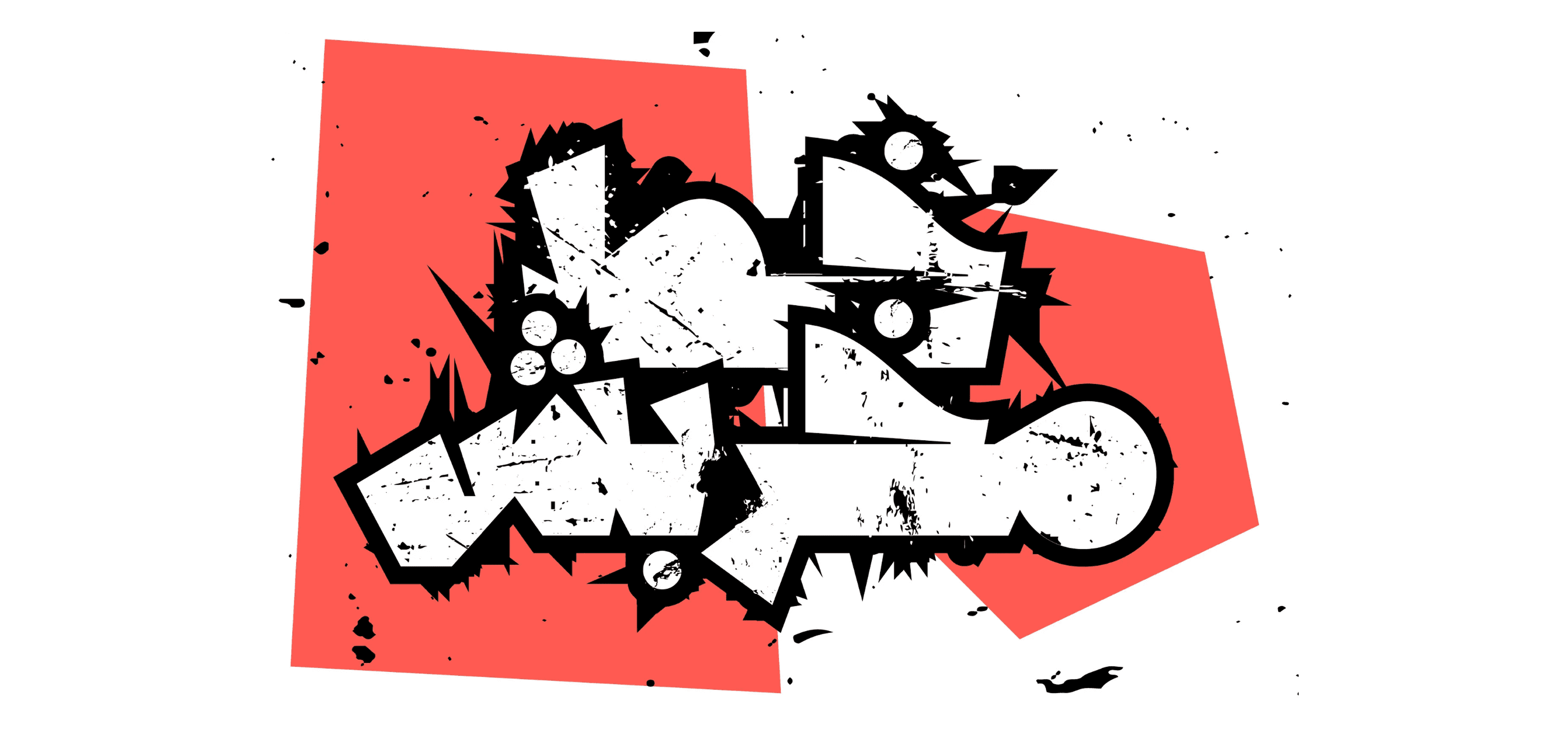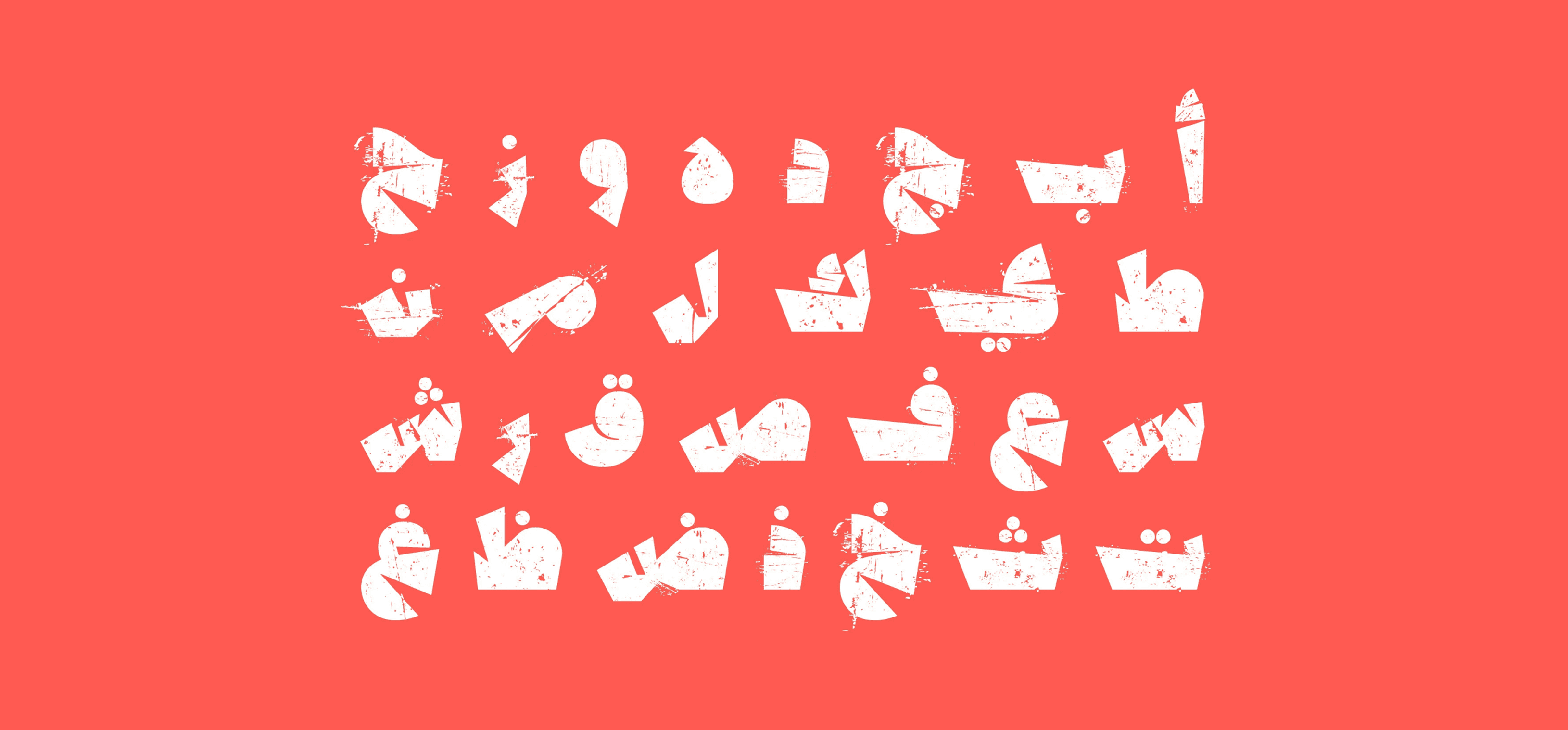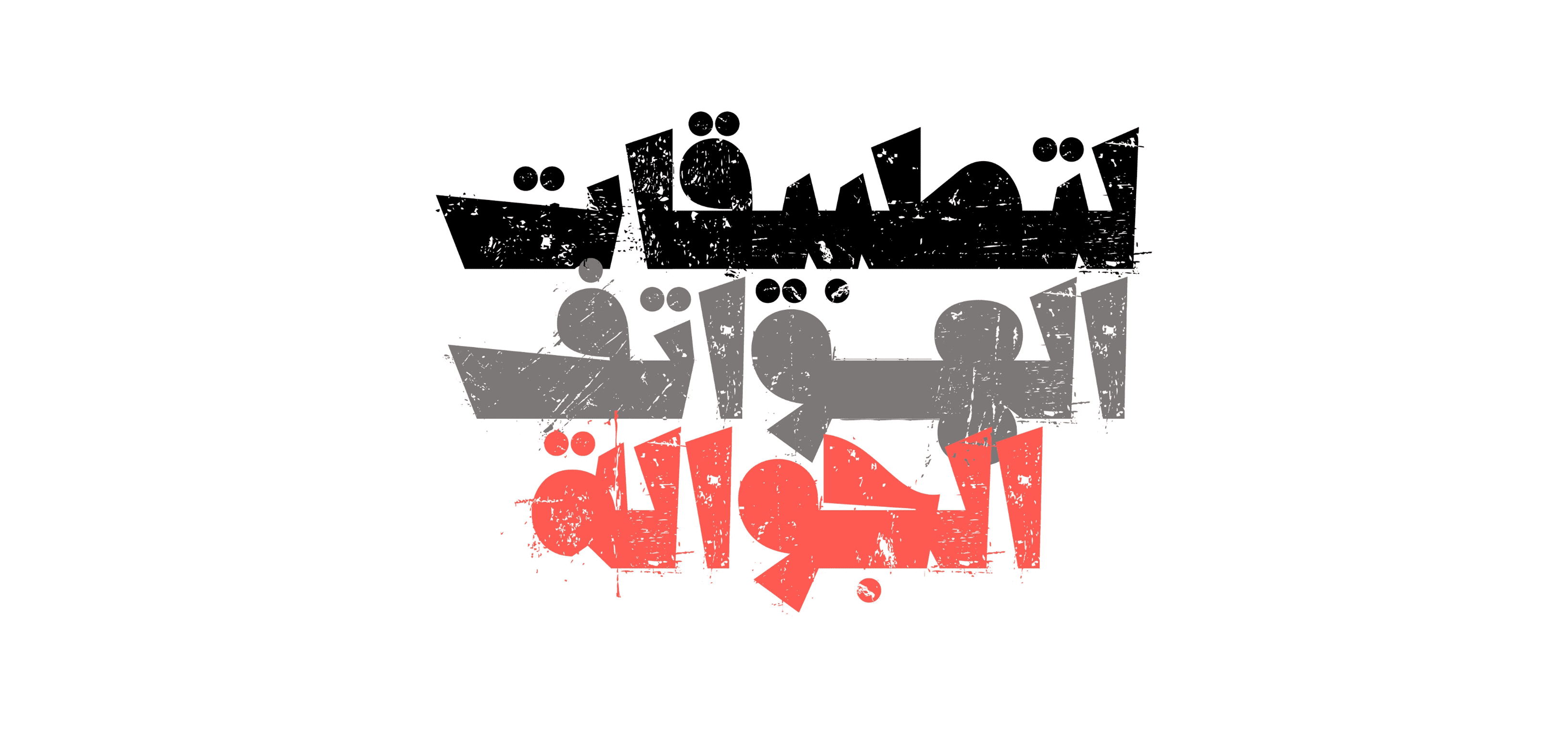
خط Qafashat (وهي كلمة عربية تعني "نُكَت" أو "تعليقات لاذعة") هو خط عرض عربي يتميز بأسلوب حرفي ثقيل ومرح مع لمسة خشنة تشبه إلى حد ما تأثير الطباعة بالحفر على الخشب (Woodcut).
يعكس تصميمه طابعًا جريئًا وبارزًا، مما يجعله مثاليًا للمشاريع التصميمية الحديثة مثل المطبوعات، المواقع الإلكترونية، وتطبيقات الهواتف المحمولة. يمتزج فيه الطابع الفني القديم مع حس فكاهي معاصر، ليمنح أي تصميم شخصية قوية ولافتة.